Được phát hành từ tháng 1/2011, Google Fonts là chuyên trang của Google về phông chữ. Website sở hữu hơn 1.000 kiểu chữ và 2.000 biểu tượng, cấp phép cho người dùng truy cập và sử dụng miễn phí. Đây là nguồn tài nguyên hữu ích cho các nhà sáng tạo, đặc biệt với nhà thiết kế website.
Trong tháng 12/2021, nền tảng đã bổ sung thêm tính năng “Fonts Knowledge” nhằm cung cấp kiến thức tổng quan về phông chữ cho các nhà thiết kế. Nhóm sáng tạo của Google đã cộng tác cùng các chuyên gia về phông chữ trên khắp thế giới như Erik Spiekermann, Jessica Hische, Elliot Jay Stocks và Gerry Leonidas để đưa ra lời khuyên hữu ích cho người dùng.
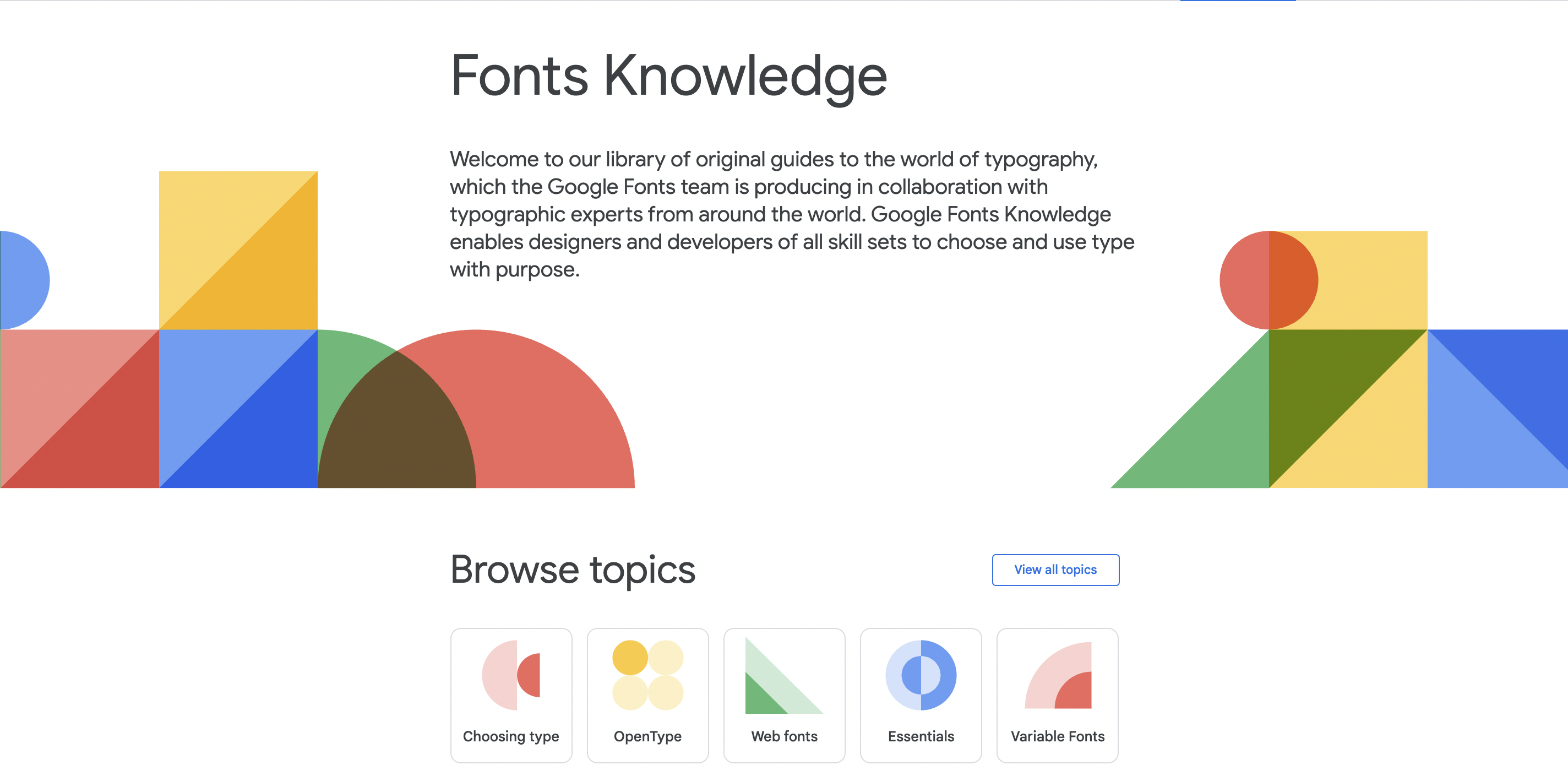
Chuyên trang Fonts Knowledge
Những bài viết trên “Fonts Knowledge” hướng dẫn độc giả cách lựa chọn phông chữ phù hợp từ cơ bản đến nâng cao. Thư viện hiện tại bao gồm hơn 100 định nghĩa thuật ngữ và 30 bài học trải rộng trên ba mô-đun: Giới thiệu các loại phông chữ, Cách chọn phông chữ và Sử dụng phông chữ. Các nội dung này sẽ được cập nhật liên tục dựa trên xu hướng mới và những phản hồi của người sử dụng.
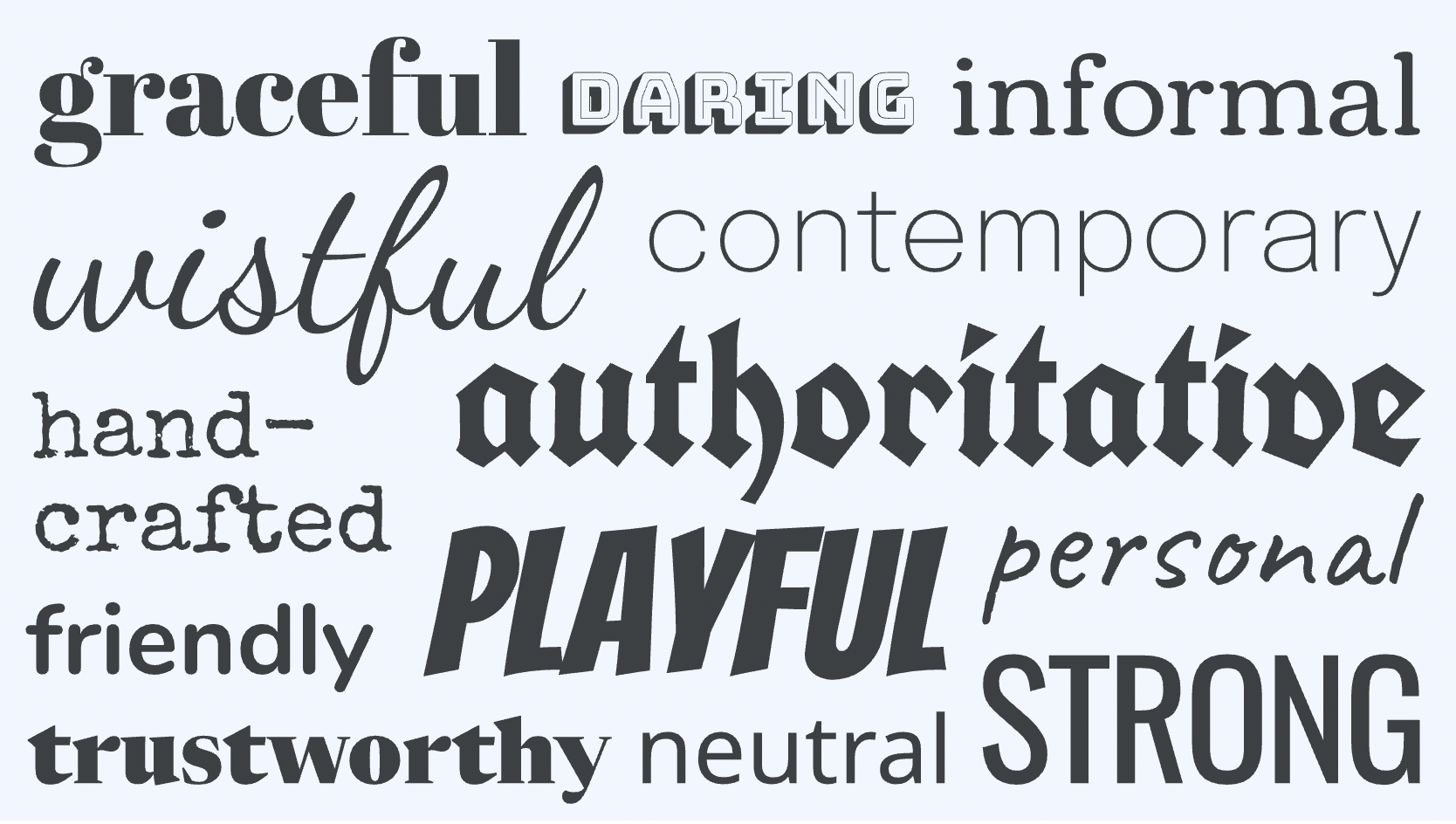
Những kiểu chữ khác nhau với tinh thần khác nhau
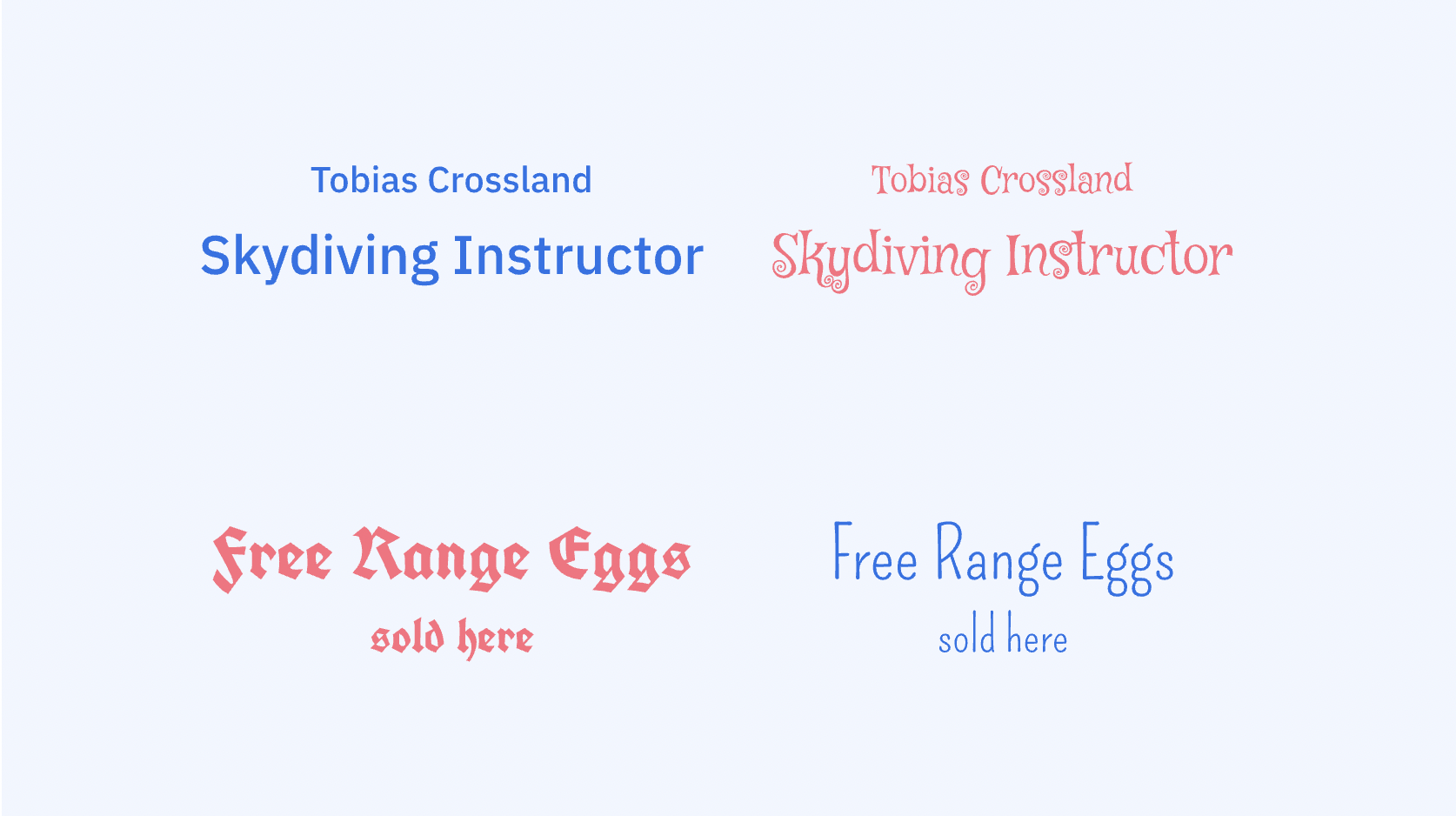
Kết hợp sử dụng màu sắc và kiểu chữ
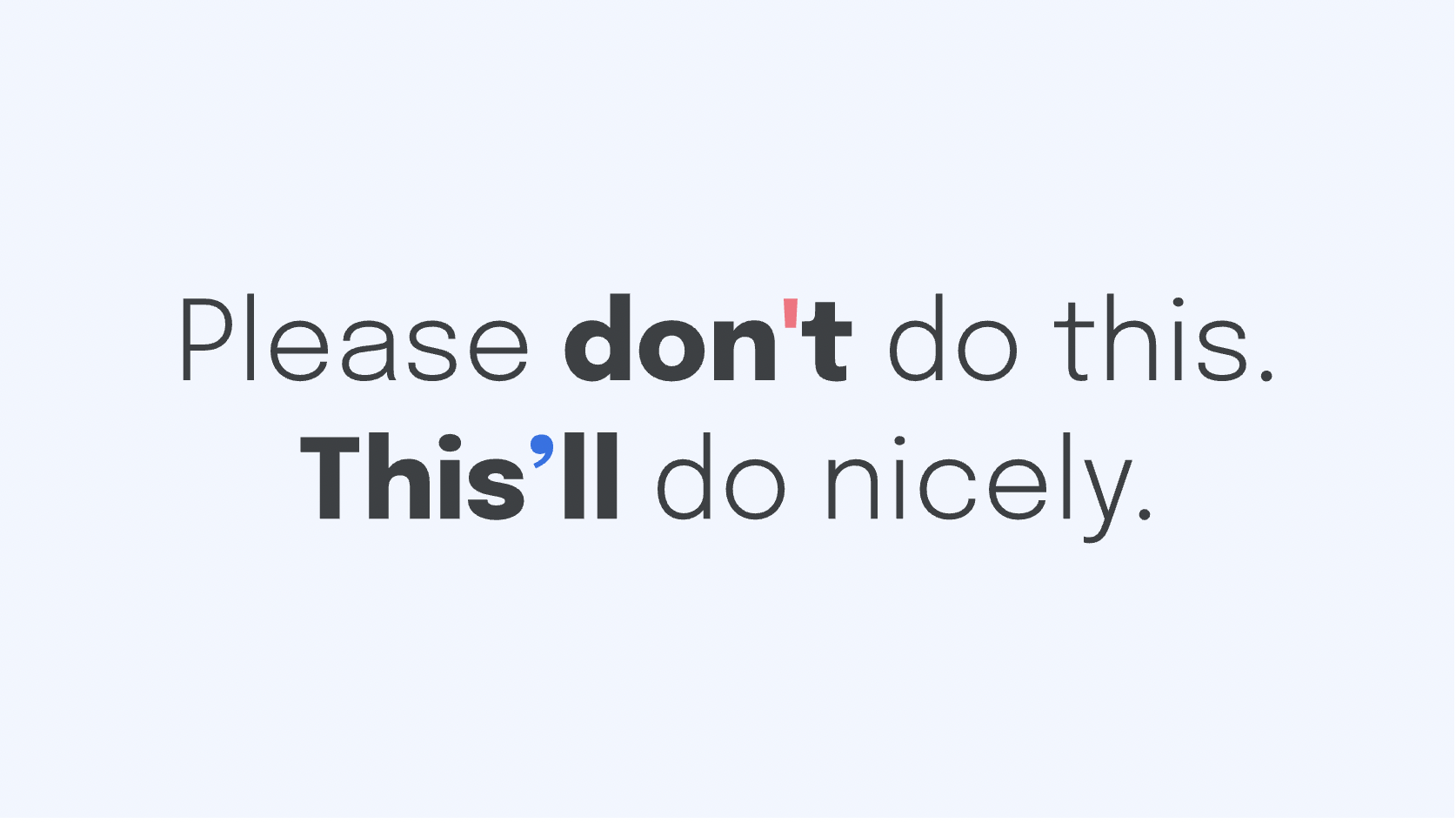
Hình dáng dấu nháy cũng ảnh hưởng đến thiết kế
Elliot Jay Stocks, Chuyên gia nhóm sáng tạo Fonts Knowledge cho biết: “Các kiến thức trên Fonts Knowledge hiện tại tập trung nhiều vào tiếng Latinh. Chúng tôi đã có kế hoạch để phát triển thêm các nội dung hữu ích cho những hệ thống phông chữ khác trên thế giới”.